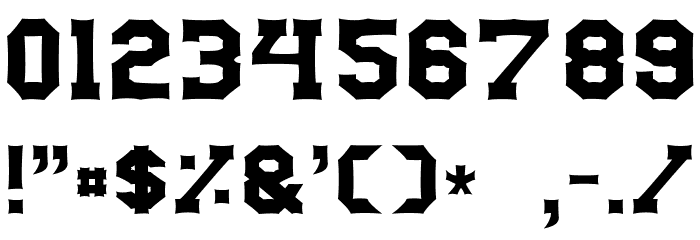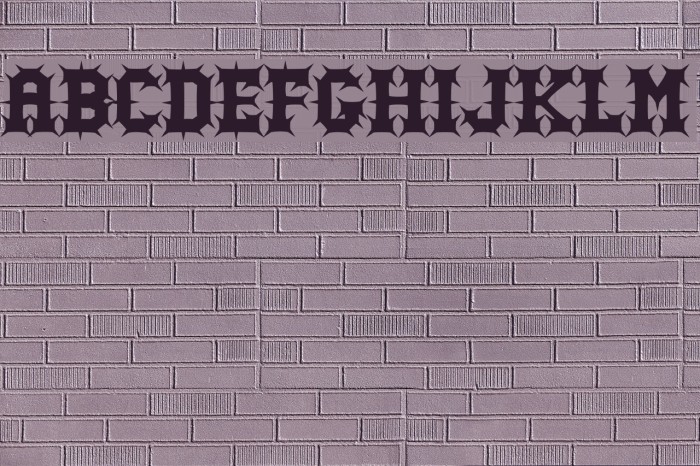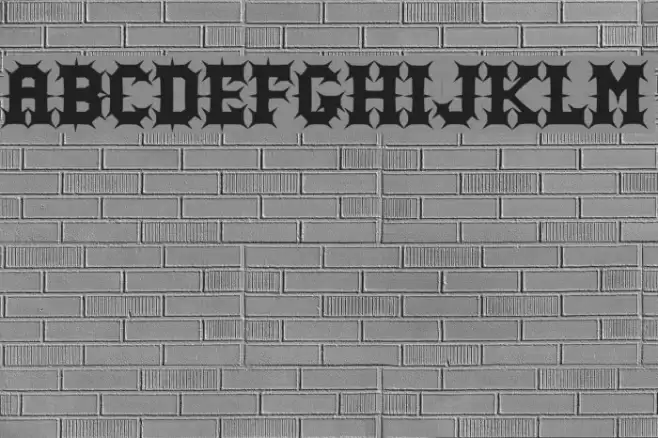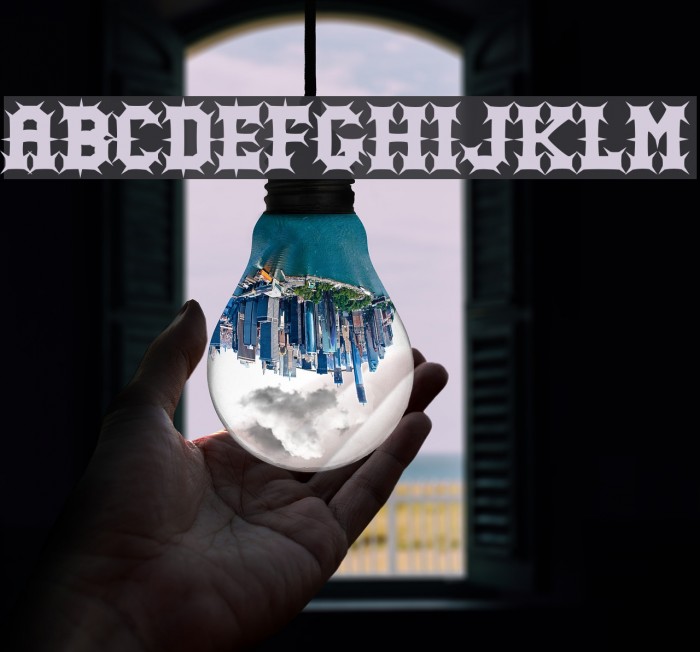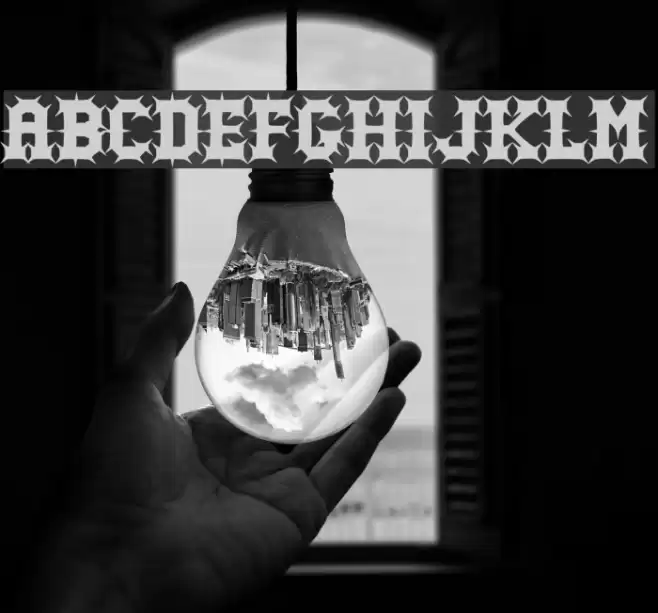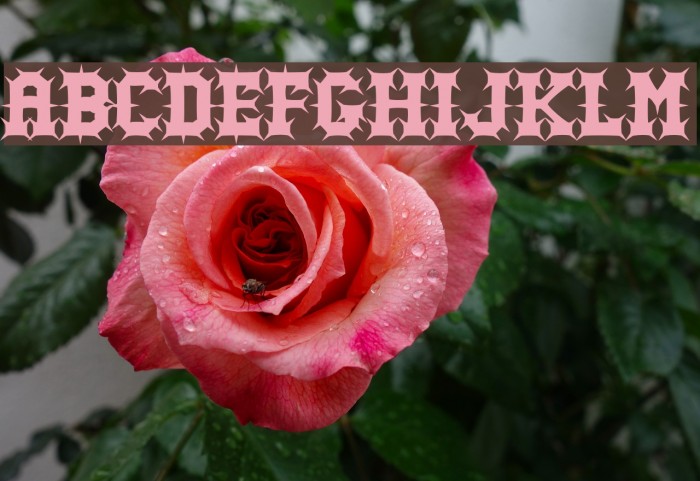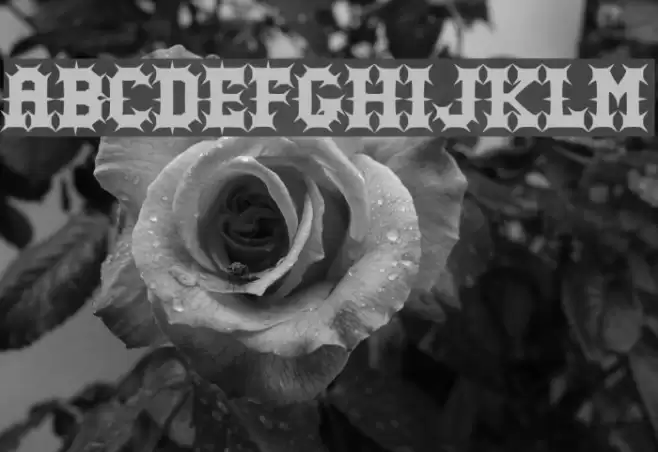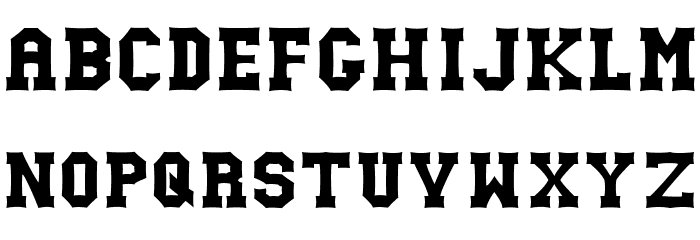
Gutcruncher Normal Font
| Estilo geral | Gothic, Dramatic |
| Projetos propostos | Ideal for album covers, posters, branding for edgy or alternative products, and any design requiring a dramatic, gothic flair. |